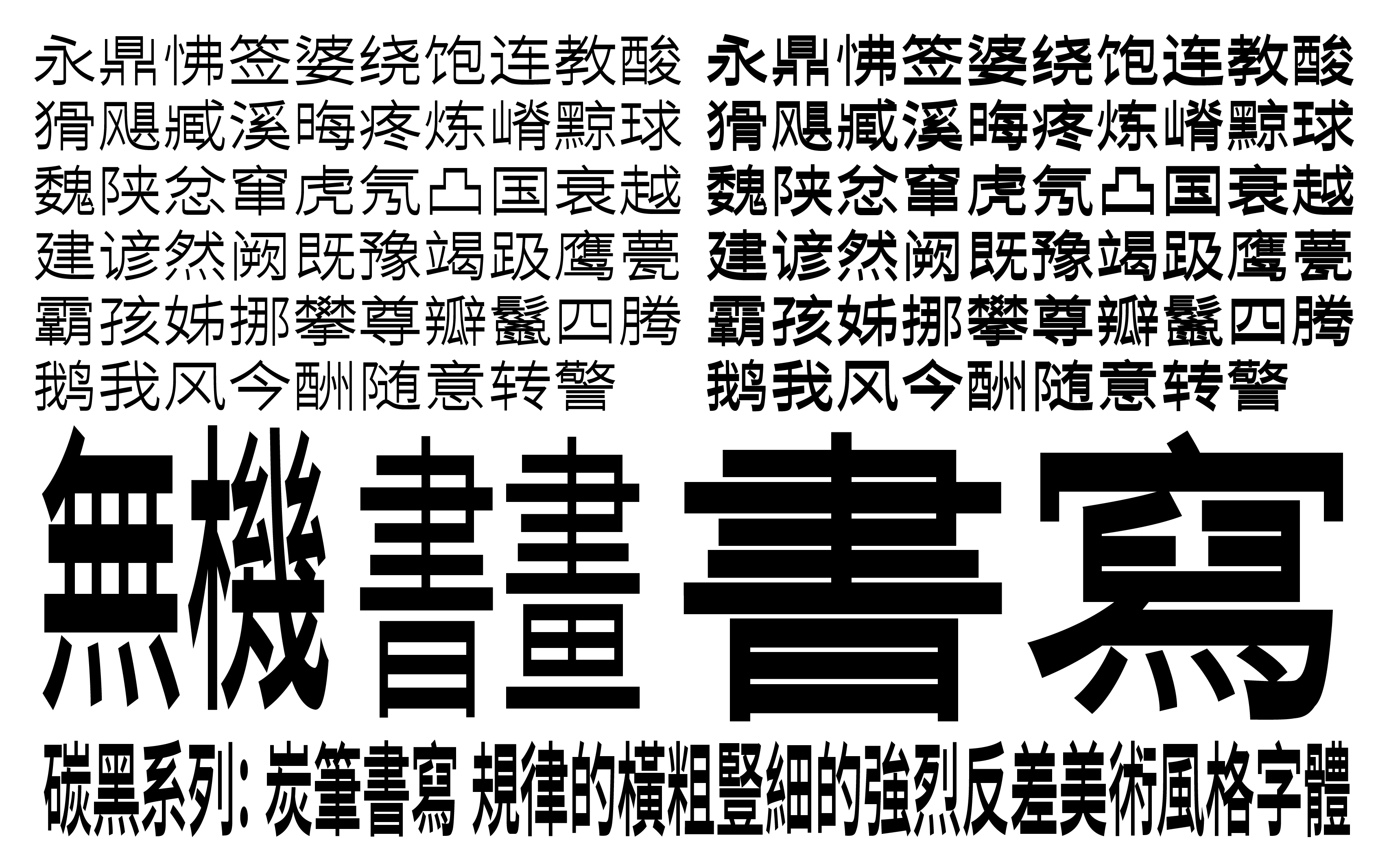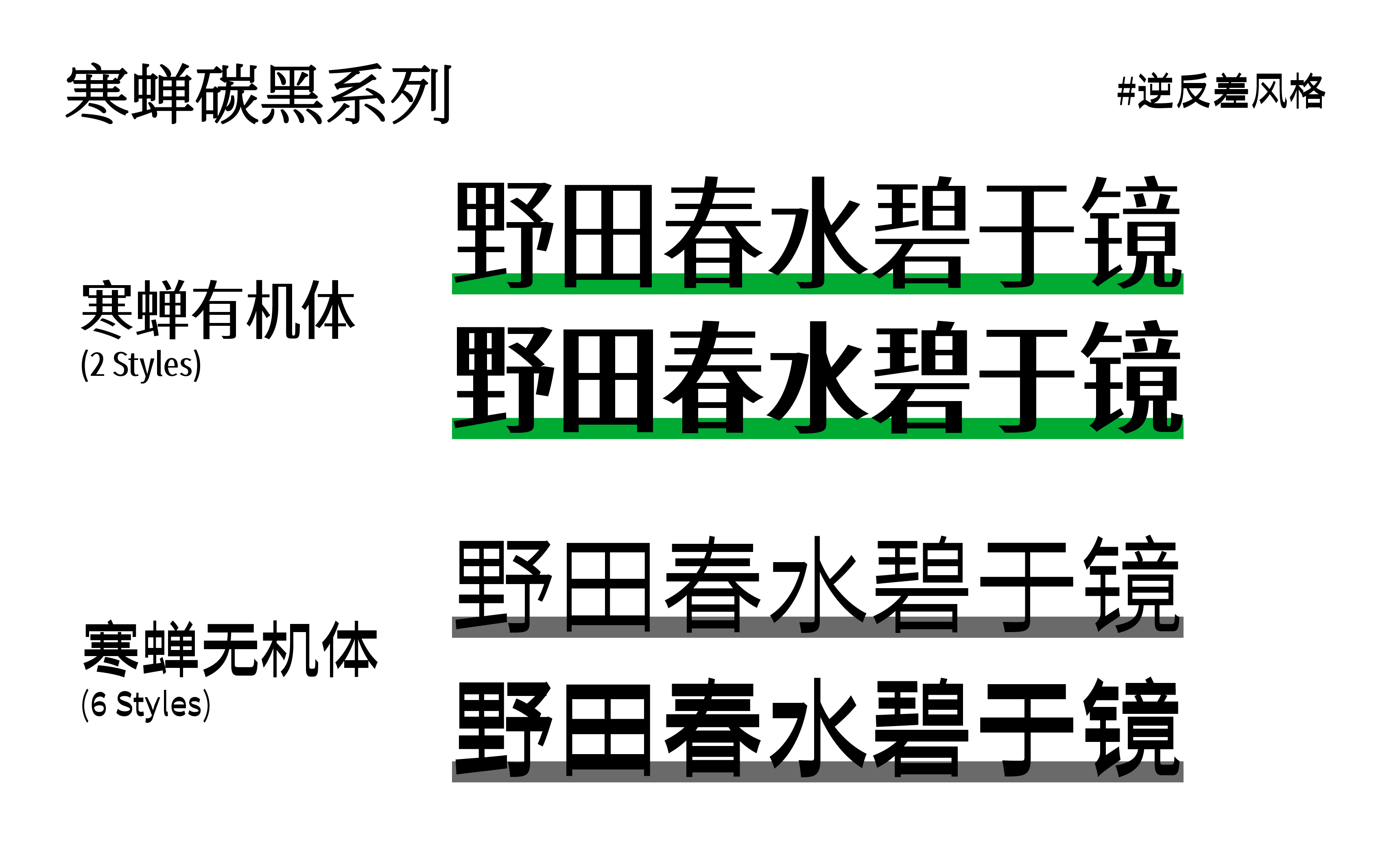
寒蝉碳黑体(Chill TanHei)是一款基于思源黑体开发的,具有逆反差风格的免费可商用美术黑体,可分为有机体和无机体两大分支。
所谓逆反差风格指的是,传统字体大多以“横细竖粗”的设计为主,而寒蝉碳黑体则采用的是相反的“横粗竖细”,营造出了一种炭笔书写的复古美术质感。
再说一下两大分支,有机体(ChillOrganic)有 2 个字重,柔和的笔画弧度与有机曲线,比较适合海报、品牌标题等场景;无机体(ChillInorganic)虽然也是 2 个字重,但有 6 种风格,笔画硬朗锐利,更适合科技、赛博朋克、潮流视觉等场景。不过这两种分支都不建议密集型正文排版,尤其是小字号的情况下,因为逆反差风格很容易增加阅读疲劳。